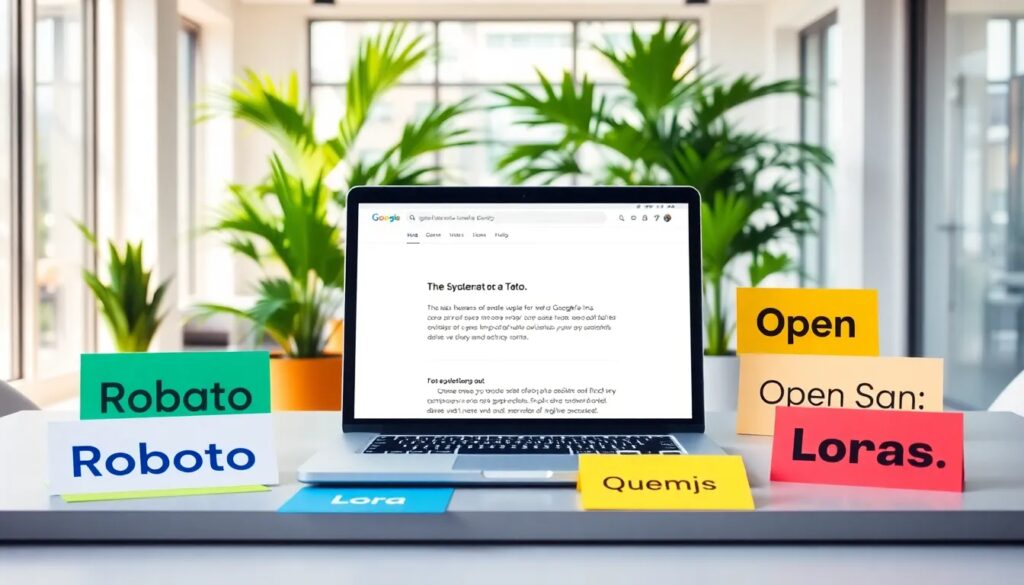
Las mejores Google Fonts para tu página web
Google Fonts se ha convertido en una herramienta esencial para diseñadores y desarrolladores web que buscan mejorar la estética y la legibilidad de sus sitios. Con una amplia gama de opciones disponibles, elegir la mejor fuente para tu proyecto puede hacer la diferencia en la experiencia del usuario.
En este artículo, exploraremos las 40 mejores Google Fonts, brindando recomendaciones y consejos sobre cómo seleccionar las fuentes adecuadas para optimizar el diseño de tu página web.
¿Para qué sirven las Google Fonts?
Las Google Fonts son un conjunto de tipografías de código abierto que cualquier persona puede utilizar de manera gratuita. Su propósito principal es proporcionar opciones de tipografía de alta calidad que sean fácilmente accesibles mediante CSS.
Estas fuentes no solo mejoran la apariencia de un sitio web, sino que también contribuyen a la legibilidad del contenido, lo que es crucial para mantener la atención de los usuarios. Gracias a su integración sencilla, puedes personalizar tu sitio web con solo unas líneas de código.
- Amplia variedad de estilos y diseños.
- Gratuitas y de fácil acceso para todos.
- Optimización de la experiencia visual del usuario.
- Compatibles con múltiples plataformas y navegadores.
Además, al utilizar Google Fonts, puedes estar seguro de que tus fuentes se cargarán rápida y eficientemente, mejorando el rendimiento de tu sitio web.
¿Cuáles son las mejores Google Fonts para usar en 2026?
Con el paso del tiempo, algunas fuentes se destacan más que otras en el diseño web. A continuación, se presentan algunas de las mejores Google Fonts que seguramente serán populares en 2026:
- Roboto: Una fuente sans-serif versátil y moderna.
- Open Sans: Ideal para interfaces y textos largos.
- Lato: Con un diseño limpio y amigable.
- Merriweather: Perfecta para mejorar la legibilidad en pantallas.
- Alegreya: Una opción elegante y dinámica para el diseño editorial.
Además de estas, hay muchas otras fuentes que podrían surgir, así que mantenerse actualizado sobre las tendencias de tipografía es clave para cualquier diseñador.
¿Cómo elegir las fuentes de Google adecuadas para tu sitio web?
La elección de las fuentes adecuadas para tu sitio web debe basarse en varios factores. Aquí hay algunos consejos útiles:
- Considera la legibilidad: Asegúrate de que la fuente sea fácil de leer en diferentes tamaños y en varios dispositivos.
- Estilo y tono: Elige una fuente que complemente la identidad de tu marca.
- Combinaciones de fuentes: Experimenta con diferentes combinaciones para encontrar la que mejor se adapte a tu diseño.
Recuerda que no todas las fuentes son adecuadas para todos los propósitos, así que es esencial hacer pruebas antes de tomar una decisión final. Considera también el contexto de uso; por ejemplo, una fuente para un blog puede no funcionar bien en un e-commerce.
¿Qué tipografías de Google son las más legibles?
La legibilidad es fundamental en el diseño web, especialmente para sitios que contienen mucho texto. Algunas de las tipografías más legibles son:
- Source Sans Pro: Una fuente sans-serif que ofrece claridad y modernidad.
- PT Sans: Equilibrada y fácil de leer, ideal para texto en pantalla.
- Nunito: Con un diseño suave que mejora la legibilidad.
- Work Sans: Perfecta tanto para títulos como para el cuerpo del texto.
El uso de estas tipografías puede aumentar significativamente la experiencia del usuario, haciendo que tu contenido sea accesible para una audiencia más amplia.
¿Cómo integrar Google Fonts en tu proyecto digital?
Integrar Google Fonts en tu proyecto es un proceso sencillo. Existen dos métodos principales:
- Usar la API de Google Fonts: Puedes incluir las fuentes directamente en el HTML de tu página mediante un enlace en la sección
<head>. - Usar @font-face en CSS: Si prefieres tener más control sobre las fuentes, puedes descargarlas y utilizarlas localmente.
Asegúrate de seguir las instrucciones detalladas en el sitio oficial de Google Fonts para evitar problemas de carga y asegurar que las fuentes se muestren correctamente en todos los navegadores.
¿Existen combinaciones recomendadas de fuentes en Google Fonts?
Algunas combinaciones son clásicas y han demostrado ser efectivas. Aquí hay algunas sugerencias que puedes considerar:
- Alegreya + Source Sans Pro: Para un diseño dinámico y legible.
- Lato + Merriweather: Una combinación que ofrece elegancia y claridad.
- Roboto + Open Sans: Ideal para proyectos modernos y minimalistas.
Experimentar con diferentes combinaciones te permitirá encontrar la mejor opción para tu sitio web, asegurando que la tipografía cumpla su función de comunicar de manera efectiva.
¿Cuáles son las ventajas de usar Google Fonts en diseño web?
Implementar Google Fonts trae consigo múltiples ventajas, entre las que se destacan:
- Gratuidad: Todas las fuentes son gratuitas y de uso ilimitado.
- Variedad: Hay miles de fuentes disponibles, lo que permite una personalización única.
- Facilidad de integración: Se pueden agregar fácilmente a cualquier proyecto con solo unas líneas de código.
- Actualizaciones constantes: Google sigue ampliando su biblioteca de fuentes, ofreciendo nuevas opciones de manera regular.
Estas ventajas hacen de Google Fonts una elección ideal para diseñadores que buscan mejorar la estética y funcionalidad de sus proyectos web.
La elección de las mejores Google Fonts para tu página web puede ser crucial para el éxito de tu proyecto. Recuerda siempre seleccionar fuentes que no solo sean visualmente atractivas, sino que también mejoren la legibilidad y la experiencia del usuario.